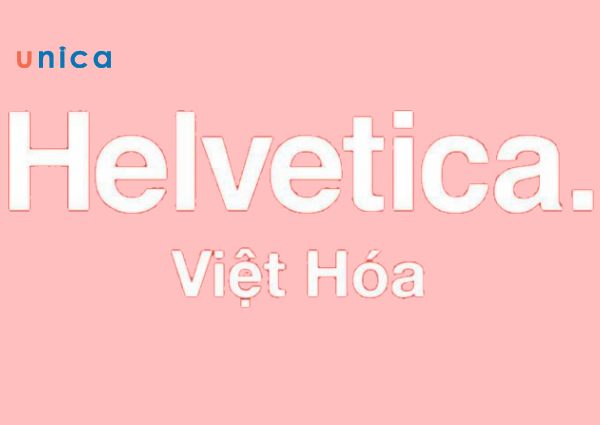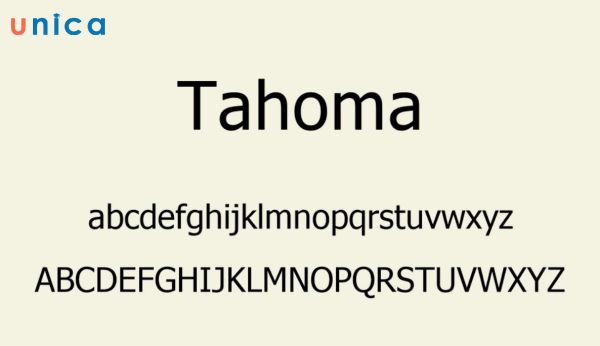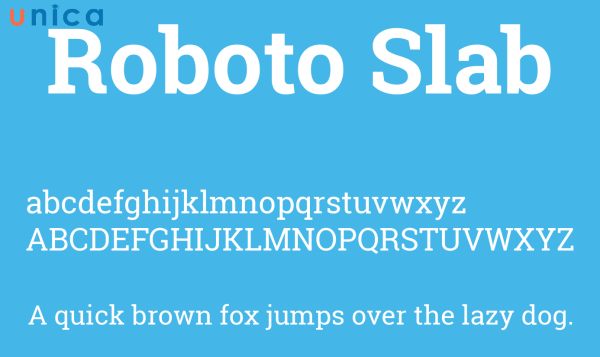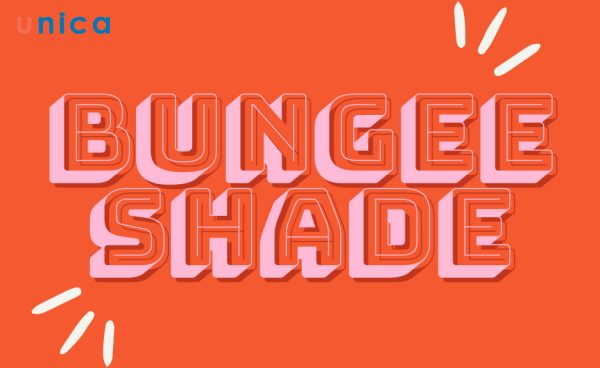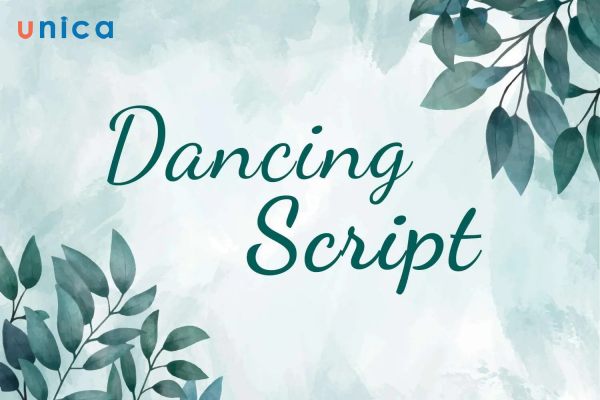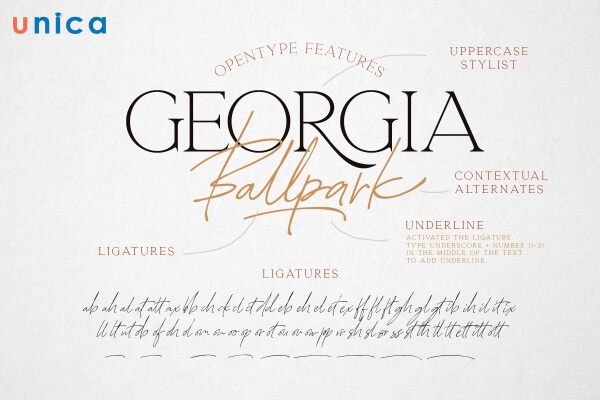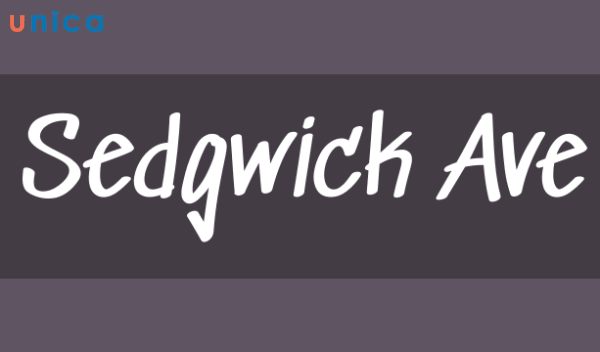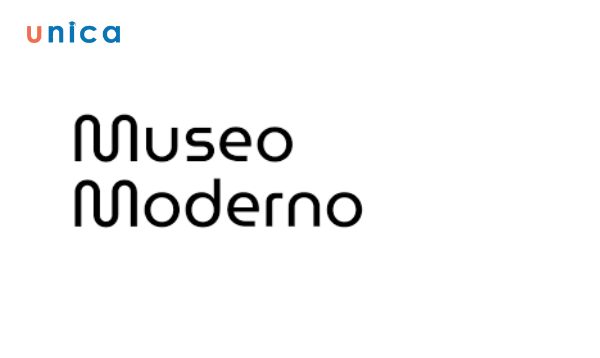
Top các font chữ đẹp tiếng việt giúp văn bản đẹp, thu hút hơn
Bạn đang tìm kiếm các font chữ đẹp tiếng Việt để làm cho văn bản của bạn trở nên đẹp mắt, thu hút và chuyên nghiệp hơn? Bạn đang băn khoăn không biết nên chọn font chữ nào cho phù hợp với mục đích và nội dung của bạn? Bạn đang gặp phải những lỗi font chữ tiếng Việt khi sử dụng word? Nếu bạn có những thắc mắc này, hãy cùng theo dõi bài viết dưới đây để tìm hiểu về top các font chữ tiếng Việt năm 2023 giúp văn bản đẹp, thu hút hơn. Chúng tôi sẽ giới thiệu cho bạn về tầm quan trọng của việc lựa chọn font chữ đẹp trong word, giới thiệu một số font chữ tiếng Việt cho các loại văn bản khác nhau, chỉ ra những lỗi font chữ tiếng Việt thường gặp và đưa ra một số lưu ý khi lựa chọn font chữ đẹp. Hãy cùng bắt đầu nhé!
Tại sao cần phải lựa chọn Font chữ đẹp trong word?
Font chữ là một yếu tố quan trọng trong việc trình bày văn bản. Font chữ không chỉ ảnh hưởng đến thẩm mỹ của văn bản, mà còn ảnh hưởng đến tính hiệu quả, sự truyền tải và sự nhận thức của người đọc. Một số lý do để bạn cần phải lựa chọn font chữ đẹp trong word là:
Tăng tính ảnh hưởng và sự chuyên nghiệp
Font chữ có thể tạo ra một ấn tượng ban đầu cho người đọc về văn bản của bạn. Một font chữ đẹp sẽ giúp văn bản của bạn trở nên hấp dẫn, uy tín và chuyên nghiệp hơn. Ngược lại, một font chữ xấu sẽ làm giảm giá trị của văn bản, gây ra sự nhàm chán, thiếu tin cậy và thiếu tôn trọng cho người đọc.
Font chữ có thể tạo ra một ấn tượng ban đầu cho người đọc về văn bản
Tạo điểm nhấn và thể hiện cá tính
Font chữ cũng có thể giúp bạn tạo ra những điểm nhấn cho văn bản, làm nổi bật những thông tin quan trọng, những ý kiến cá nhân hoặc những cảm xúc của bạn. Bạn có thể sử dụng các font chữ khác nhau để thể hiện cá tính, phong cách và sở thích của bạn.
Ví dụ, bạn có thể dùng các font chữ hiện đại, sáng tạo và trẻ trung để thể hiện sự năng động và mới mẻ; hoặc bạn có thể dùng các font chữ cổ điển, thanh lịch và trang nhã để thể hiện sự sang trọng và tinh tế.
Tăng sự thu hút
Font chữ đẹp tiếng việt cũng có thể giúp bạn thu hút sự quan tâm và chú ý của người đọc. Một font chữ đẹp sẽ làm cho văn bản của bạn trở nên sinh động, phong phú và hấp dẫn hơn. Người đọc sẽ có xu hướng muốn đọc tiếp và khám phá thêm văn bản của bạn. Một font chữ xấu sẽ làm cho văn bản của bạn trở nên đơn điệu, tẻ nhạt và nhàm chán hơn. Người đọc sẽ có xu hướng bỏ qua hoặc bỏ dở văn bản của bạn.
Font chữ cũng có thể giúp bạn thu hút sự quan tâm và chú ý của người đọc
Giới thiệu một số font chữ đẹp tiếng Việt
Trên word, bạn có thể tìm thấy rất nhiều font chữ đẹp tiếng Việt cho các loại văn bản khác nhau. Dưới đây là một số font chữ tiếng Việt mà chúng tôi muốn giới thiệu cho bạn:
Phông chữ đẹp trong word dành cho văn bản
Nếu bạn muốn viết các loại văn bản như báo cáo, luận văn, bài viết, thư từ, email,… bạn nên chọn các font chữ dễ đọc, rõ ràng và trang trọng. Một số font chữ đẹp trong word dành cho văn bản là:
Be Vietnam
Be Vietnam là một font chữ sans serif được thiết kế bởi Nguyễn Đức Hiếu. Font chữ này có 8 kiểu khác nhau, từ Extra Light đến Extra Bold. Font chữ này có thể hỗ trợ tiếng Việt và nhiều ngôn ngữ khác. Font chữ đẹp word này có dáng vẻ hiện đại, thanh thoát và cân đối. Font chữ này phù hợp cho các văn bản mang tính truyền thông, quảng cáo và thương mại.
Be Vietnam là một font chữ sans serif được thiết kế bởi Nguyễn Đức Hiếu
Open Sans
Open Sans là một font chữ sans serif được thiết kế bởi Steve Matteson. Font chữ đẹp tiếng việt này có 10 kiểu khác nhau, từ Light đến Extra Bold. Font chữ này có thể hỗ trợ tiếng Việt và nhiều ngôn ngữ khác. Open Sans có dáng vẻ trung tính, thân thiện và linh hoạt. Font chữ này phù hợp cho các văn bản mang tính thông tin, giáo dục và khoa học.
Roboto
Roboto là một trong số các font chữ tiếng việt đẹp có sẵn trong word, nó thuộc font chữ sans serif được thiết kế bởi Christian Robertson. Font chữ này có 12 kiểu khác nhau, từ Thin đến Black. Font chữ này có thể hỗ trợ tiếng Việt và nhiều ngôn ngữ khác. Roboto có dáng vẻ hiện đại, rõ ràng và tự nhiên nên phù hợp cho các văn bản mang tính công nghệ, kỹ thuật và kinh doanh.
Roboto có dáng vẻ hiện đại, rõ ràng và tự nhiên
Source Sans Pro
Source Sans Pro là một font chữ sans serif được thiết kế bởi Paul D. Hunt. Font chữ này có 12 kiểu khác nhau, từ Extra Light đến Black. Font chữ này có thể hỗ trợ tiếng Việt và nhiều ngôn ngữ khác. Font chữ này có dáng vẻ đơn giản, thanh lịch và hiệu quả. Source Sans Pro phù hợp cho các văn bản mang tính sáng tạo, nghệ thuật và văn hóa.
word
Playfair Display
Playfair Display là một font chữ serif được thiết kế bởi Claus Eggers Sørensen. Font chữ đẹp tiếng việt này có 6 kiểu khác nhau, từ Regular đến Black. Font chữ này có thể hỗ trợ tiếng Việt và nhiều ngôn ngữ khác. Font này có dáng vẻ cổ điển, sang trọng và quý phái nên phù hợp cho các văn bản mang tính lịch sử, văn học và thời trang.
Playfair Display là một font chữ serif được thiết kế bởi Claus Eggers Sørensen
Bookman
Bookman là một font chữ serif được thiết kế bởi Alexander Phemister. Font chữ này có 4 kiểu khác nhau, từ Regular đến Bold Italic. Font chữ này có thể hỗ trợ tiếng Việt và nhiều ngôn ngữ khác. Font chữ này có dáng vẻ truyền thống, tinh tế và uyển chuyển. Font chữ Bookman phù hợp cho các văn bản mang tính giáo dục, tri thức và báo chí.
Museo Moderno
Museo Moderno là một font chữ serif được thiết kế bởi Omnibus-Type. Font chữ này có 14 kiểu khác nhau, từ Thin đến Heavy. Font chữ này có thể hỗ trợ tiếng Việt và nhiều ngôn ngữ khác. Font chữ này có dáng vẻ hiện đại, độc đáo và nghệ thuật. Font chữ này phù hợp cho các văn bản mang tính sáng tạo, thiết kế và nghệ thuật.
Museo Moderno là một font chữ serif được thiết kế bởi Omnibus-Type
Noto Serif
Noto Serif là một font chữ serif được thiết kế bởi Google. Font chữ này có 4 kiểu khác nhau, từ Regular đến Bold Italic. Font chữ này có thể hỗ trợ tiếng Việt và nhiều ngôn ngữ khác. Font chữ đẹp tiếng việt này có dáng vẻ đa dạng, cân bằng và hài hòa nên phù hợp cho các văn bản mang tính đa văn hóa, đa ngôn ngữ và đa phương tiện.
Sedgwick Ave
Sedgwick Ave là một font chữ handwritten được thiết kế bởi Google. Font chữ này có 2 kiểu khác nhau là Regular và Display. Font chữ này có thể hỗ trợ tiếng Việt và nhiều ngôn ngữ khác. Font chữ này có dáng vẻ thân thiện, gần gũi và cá nhân nên phù hợp cho các văn bản mang tính giao tiếp, thư từ và blog.
Sedgwick Ave là một font chữ handwritten được thiết kế bởi Google
Amatic SC
Amatic SC là một font chữ viết tay trong word được thiết kế bởi Vernon Adams và Ben Nathan. Font chữ này có 2 kiểu khác nhau là Regular và Bold. Font chữ này có thể hỗ trợ tiếng Việt và nhiều ngôn ngữ khác. Amatic SC này có dáng vẻ độc lập, sôi nổi và năng động nên phù hợp cho các văn bản mang tính giải trí, du lịch hoặc nội dung viết cho trẻ em.
Patrick Hand
Patrick Hand là một font chữ handwritten được thiết kế bởi Patrick Wagesreiter. Font chữ này chỉ có một kiểu duy nhất là Regular. Patrick Hand có thể hỗ trợ tiếng Việt và nhiều ngôn ngữ khác. Font chữ này có dáng vẻ tự nhiên, dễ thương và lãng mạn. Font chữ đẹp tiếng việt này phù hợp cho các văn bản mang tính cảm xúc, tình cảm và nhật ký.
Patrick Hand là một font chữ handwritten được thiết kế bởi Patrick Wagesreiter
Courier new
Courier new là một font chữ monospaced được thiết kế bởi Howard Kettler. Font chữ này có 4 kiểu khác nhau, từ Regular đến Bold Italic. Courier new có thể hỗ trợ tiếng Việt và nhiều ngôn ngữ khác. Font chữ này có dáng vẻ cổ điển, chính thức và chuyên nghiệp. Font chữ này phù hợp cho các văn bản mang tính kỹ thuật, lập trình và tài liệu.
Verdana
Verdana là một font chữ sans serif được thiết kế bởi Matthew Carter. Phông chữ tiếng việt trong word này có 4 kiểu khác nhau, từ Regular đến Bold Italic. Font chữ này có thể hỗ trợ tiếng Việt và nhiều ngôn ngữ khác. Font chữ này đem tới cảm giác rộng rãi, minh bạch và dễ đọc. Font chữ đẹp tiếng việt Verdana phù hợp cho các văn bản mang tính trực quan, trình chiếu và web.
Georgia
Trong số các font chữ tiếng việt trong word, Georgia là một font chữ serif được thiết kế bởi Matthew Carter. Font chữ này có 4 kiểu khác nhau, từ Regular đến Bold Italic. Font chữ này có thể hỗ trợ tiếng Việt và nhiều ngôn ngữ khác. Font chữ này có dáng vẻ cổ điển, thanh thoát và tao nhã nên phù hợp cho các văn bản mang tính văn học, văn hóa và nghệ thuật.
Georgia là một font chữ serif được thiết kế bởi Matthew Carter
Các kiểu chữ đẹp trong word cho thiết kế
Nếu bạn muốn thiết kế các loại văn bản như poster, banner, logo, slogan,… bạn nên chọn các font chữ độc đáo, sáng tạo và ấn tượng. Một số font chữ đẹp trong word cho thiết kế là:
Bangers
Bangers là một font chữ comic được thiết kế bởi Vernon Adams. Font chữ này chỉ có một kiểu duy nhất là Regular. Font chữ đẹp tiếng việt này có thể hỗ trợ tiếng Việt và nhiều ngôn ngữ khác. Bangers có kiểu dáng mạnh mẽ, nổi bật và hài hước. Font chữ này phù hợp cho các văn bản mang tính giải trí, hoạt hình và game.
Bangers là một font chữ comic được thiết kế bởi Vernon Adams
Lobster
Lobster là một font chữ script được thiết kế bởi Pablo Impallari. Font chữ này chỉ có một kiểu duy nhất là Regular. Lobster có thể hỗ trợ tiếng Việt và nhiều ngôn ngữ khác. Font chữ này có dáng vẻ uốn lượn, duyên dáng và lôi cuốn nên phù hợp cho các văn bản viết về thời trang, ẩm thực hoặc lễ hội.
Dancing Script
Trong số các kiểu chữ đẹp trong word, Dancing Script là một font chữ script được thiết kế bởi Impallari Type. Font chữ này có 2 kiểu khác nhau là Regular và Bold. Font chữ này có thể hỗ trợ tiếng Việt và nhiều ngôn ngữ khác. Dancing Script có dáng vẻ hiện đại, rõ ràng và linh hoạt. Font chữ đẹp tiếng việt này phù hợp cho các tài liệu mang tính công nghệ, kỹ thuật và kinh doanh.
Dancing Script là một font chữ script được thiết kế bởi Impallari Type
Pacifico
Pacifico là một font chữ tiếng Việt thân thiện và phong cách, thích hợp cho các tiêu đề, tiêu đề trang và các yếu tố thiết kế sáng tạo khác. Với đường nét mềm mại và hiện đại, Pacifico thường được sử dụng trong các thiết kế liên quan đến nghệ thuật, thẩm mỹ và phong cách cá nhân.
Bungee Shade
Bungee Shade là một font chữ tiếng Việt độc đáo và nổi bật với những nét chữ hình khối. Với sự kết hợp của các đường nét mạnh mẽ và sự sáng tạo trong thiết kế, Bungee Shade thường được ưa chuộng trong các dự án liên quan đến thiết kế đồ họa và trang trí.
Bungee Shade là một font chữ tiếng Việt độc đáo và nổi bật với những nét chữ hình khối
Saira Stencil One
Saira Stencil One là một font chữ đẹp tiếng Việt mang phong cách stencil, tạo nên sự độc đáo và nổi bật trong các thiết kế. Với các đường nét mạnh mẽ và kiểu chữ đặc biệt, Saira Stencil One thường được sử dụng để tạo điểm nhấn và tạo sự khác biệt trong các dự án thiết kế.
Srisakdi
Srisakdi là một font chữ tiếng Việt mang phong cách hiện đại và sáng tạo. Với các đường nét thanh lịch và hiện đại, Srisakdi thường được sử dụng trong các văn bản và bài thuyết trình để tạo nên sự chuyên nghiệp và sáng tạo.
Charmonman
Charmonman là một font chữ tiếng Việt với nét đẹp truyền thống và thanh lịch. Với các đường nét uốn cong và phong cách tinh tế, Charmonman thường được ưa chuộng trong các tài liệu văn bản, thư mời và các thiết kế liên quan đến văn hóa truyền thống.
Charmonman là một font chữ tiếng Việt với nét đẹp truyền thống và thanh lịch
Font chữ đẹp trên Word dành cho dân văn phòng
Dành cho dân văn phòng, việc chọn font chữ phù hợp là rất quan trọng để tạo ra văn bản chuyên nghiệp và dễ đọc. Một trong những font chữ phổ biến dành cho dân văn phòng trên Word là:
Font chữ Roboto Slab
Roboto Slab là một font chữ đẹp tiếng Việt đơn giản và dễ đọc, với các đường nét thanh lịch và chữ viết rõ ràng. Với phong cách hiện đại và trang nhã, Roboto Slab thường được sử dụng trong các tài liệu văn bản, báo cáo và tài liệu công việc.
Roboto Slab là một font chữ tiếng Việt đơn giản và dễ đọc, với các đường nét thanh lịch và chữ viết rõ ràng
Nhớ rằng, khi sử dụng font chữ trong Word, bạn cũng nên kiểm tra xem font đó có bản quyền sử dụng hay không để tuân thủ các quy định liên quan đến bản quyền phần mềm.
Font chữ Bitter
Bitter là một font chữ serif được thiết kế bởi Sol Matas. Font chữ này có 4 kiểu khác nhau, từ Regular đến Bold Italic. Bitter có thể hỗ trợ tiếng Việt và nhiều ngôn ngữ khác. Font chữ này có dáng vẻ cổ điển, thanh thoát và tao nhã nên phù hợp cho các tài liệu mang tính văn học, văn hóa và nghệ thuật.
Font chữ Lora
Lora là một font chữ serif được thiết kế bởi Cyreal. Font chữ đẹp tiếng việt này có 4 kiểu khác nhau, từ Regular đến Bold Italic. Font chữ này có thể hỗ trợ tiếng Việt và nhiều ngôn ngữ khác. Font chữ này có dáng vẻ trang nhã, cân bằng và hài hòa nên phù hợp cho các tài liệu mang tính thông tin, giáo dục và khoa học.
Lora là một font chữ serif được thiết kế bởi Cyreal
Times New Roman
Times New Roman là một font chữ serif được thiết kế bởi Stanley Morison. Font chữ này có 4 kiểu khác nhau, từ Regular đến Bold Italic. Font chữ này có thể hỗ trợ tiếng Việt và nhiều ngôn ngữ khác. Font chữ này có dáng vẻ truyền thống, chính thức và uy tín. Times New Roman phù hợp cho các tài liệu mang tính lịch sử, báo chí và tôn giáo.
Arial
Arial là một font chữ sans serif được thiết kế bởi Monotype Corporation. Font chữ đẹp tiếng việt này có 4 kiểu khác nhau, từ Regular đến Bold Italic. Font Arial có thể hỗ trợ tiếng Việt và nhiều ngôn ngữ khác. Font này có dáng vẻ đơn giản, minh bạch và dễ đọc nên phù hợp cho các tài liệu mang tính trực quan, trình chiếu và web.
Tahoma
Tahoma là một font chữ sans serif được thiết kế bởi Matthew Carter. Font chữ này có 2 kiểu khác nhau là Regular và Bold. Tahoma có thể hỗ trợ tiếng Việt và nhiều ngôn ngữ khác. Font chữ này khá rộng, tính chất linh hoạt nên phù hợp cho các tài liệu mang tính đa nền tảng, đa thiết bị và đa ngôn ngữ.
Tahoma là một font chữ sans serif được thiết kế bởi Matthew Carter
Calibri
Trong số những font chữ đẹp trong word, Calibri là một font chữ sans serif được thiết kế bởi Lucas de Groot. Font chữ này có 6 kiểu khác nhau, từ Light đến Bold Italic. Calibri có thể hỗ trợ tiếng Việt và nhiều ngôn ngữ khác. Font chữ đẹp tiếng việt này có dáng vẻ hiện đại, thanh lịch và trang nhã nên phù hợp cho các tài liệu mang tính sáng tạo, nghệ thuật và văn hóa.
Garamond
Garamond là một font chữ serif được thiết kế bởi Claude Garamond. Font chữ này có 4 kiểu khác nhau, từ Regular đến Bold Italic. Font Garamond có thể hỗ trợ tiếng Việt và nhiều ngôn ngữ khác. Font chữ này có dáng vẻ cổ điển, tinh tế và quý phái nên đây sẽ là sự lựa chọn phù hợp cho các tài liệu mang tính lịch sử, văn học và thời trang.
Helvetica
Helvetica là một font chữ sans serif được thiết kế bởi Max Miedinger. Font chữ này có nhiều kiểu khác nhau, từ Ultra Light đến Black. Helvetica có thể hỗ trợ tiếng Việt và nhiều ngôn ngữ khác. Font chữ này có dáng vẻ đơn giản, minh bạch và dễ đọc nên phù hợp cho các tài liệu mang tính trực quan, trình chiếu và web.
Helvetica là một font chữ sans serif được thiết kế bởi Max Miedinger
Lỗi font chữ tiếng Việt thường gặp
Khi sử dụng font chữ đẹp tiếng Việt trong word, bạn có thể gặp phải một số lỗi font chữ tiếng Việt như sau:
Font không hỗ trợ tiếng Việt
Đây là lỗi font chữ tiếng Việt khi bạn sử dụng một font chữ không có bảng mã tiếng Việt hoặc không tương thích với bộ gõ tiếng Việt của bạn. Khi đó, bạn sẽ không thể nhập được các ký tự tiếng Việt như â, ă, ê, ô, ơ, ư, đ,… hoặc các ký tự có dấu như á, à, ả, ã, ạ,… Lỗi font chữ tiếng Việt này sẽ làm cho văn bản của bạn bị sai ngữ nghĩa, khó hiểu hoặc không thể hiển thị được.
Để khắc phục lỗi font chữ tiếng Việt này, bạn nên chọn một font chữ hỗ trợ tiếng Việt hoặc cài đặt thêm font chữ tiếng Việt cho word. Bạn cũng nên kiểm tra lại bộ gõ tiếng Việt của bạn để đảm bảo rằng nó tương thích với font chữ bạn đang sử dụng.
Font không hỗ trợ tiếng Việt
Hiển thị sai ký tự tiếng Việt
Đây là lỗi font chữ tiếng Việt khi bạn sử dụng một font chữ có bảng mã tiếng Việt khác với bảng mã tiếng Việt của word hoặc của máy tính của bạn. Khi đó, bạn sẽ thấy các ký tự tiếng Việt của bạn bị thay thế bởi các ký tự khác như ?, !, #,… hoặc các ký tự lạ như Æ, Ç, Ñ,… Lỗi font chữ tiếng Việt này sẽ làm cho văn bản của bạn bị mất nội dung, sai hình thức hoặc không thể hiển thị được.
Để khắc phục lỗi font chữ tiếng Việt này, bạn nên chọn một font chữ có cùng bảng mã tiếng Việt với word hoặc với máy tính của bạn. Bạn cũng nên kiểm tra lại cài đặt ngôn ngữ và khu vực của word và của máy tính của bạn để đảm bảo rằng chúng phù hợp với font chữ mình đang sử dụng.
>>> Tất cả đều có trong cuốn sách "Sách hướng dẫn thực hành Word từ cơ bản đến nâng cao"
[blog_custom:3]
[trial-btn-v4[link=https://unica.vn/order/step1?id=2850&quantity=1][text=ĐĂNG KÝ MUA NGAY][color=#ffffff][width=275px][height=50px][bgcolor=#f26c50][newtab=true]]
Kích thước và khoảng cách chữ không chuẩn
Đây là lỗi font chữ tiếng Việt khi bạn sử dụng một font chữ có kích thước và khoảng cách chữ không phù hợp với văn bản của mình. Khi đó, bạn sẽ thấy các ký tự tiếng Việt của bạn bị quá lớn hoặc quá nhỏ, quá dày hoặc quá mỏng, quá gần hoặc quá xa nhau. Lỗi font chữ tiếng Việt này sẽ làm cho văn bản của bạn bị mất thẩm mỹ, khó đọc hoặc không đồng đều.
Để khắc phục lỗi này, bạn nên điều chỉnh kích thước và khoảng cách chữ của font đang sử dụng cho phù hợp với văn bản. Bạn có thể sử dụng các công cụ như Font, Paragraph, Styles và Format Painter trong word để thực hiện điều này. Bạn cũng nên lựa chọn một font chữ có kích thước và khoảng cách chữ chuẩn cho văn bản.
Font chữ có kích thước gặp vấn đề
Vấn đề không tương thích giữa các máy tính
Đây là lỗi font chữ tiếng Việt khi bạn gửi hoặc nhận văn bản từ một máy tính khác có cài đặt font chữ khác với máy tính của bạn. Khi đó, bạn sẽ thấy văn bản của bạn bị thay đổi font chữ, mất nội dung hoặc không thể hiển thị được trên máy tính khác. Lỗi font chữ tiếng Việt này sẽ làm cho văn bản của bạn bị mất tính nhất quán, độ tin cậy và khả năng truyền tải.
Để khắc phục lỗi font chữ tiếng Việt này, bạn nên gửi hoặc nhận văn bản dưới dạng PDF hoặc ảnh để đảm bảo rằng font chữ của bạn được giữ nguyên trên các máy tính khác. Bạn cũng nên sử dụng các font chữ tiêu chuẩn hoặc phổ biến để đảm bảo rằng các máy tính khác có thể hỗ trợ font chữ của mình.
Thiếu font chữ phù hợp
Đây là lỗi font chữ tiếng Việt khi bạn không tìm được một font chữ phù hợp với mục đích và nội dung của văn bản của bạn. Khi đó, bạn sẽ không thể tạo ra một văn bản đẹp mắt, thu hút và chuyên nghiệp. Lỗi font chữ tiếng Việt này sẽ làm cho văn bản của bạn bị thiếu sức sống, sáng tạo và ấn tượng.
Bạn nên tìm kiếm và cài đặt thêm các font chữ đẹp tiếng Việt cho word để có thể sử dụng chúng cho các văn bản của bạn. Bạn có thể tìm kiếm và cài đặt các font chữ đẹp tiếng Việt từ các trang web uy tín và miễn phí như Google Fonts, Font Squirrel, Dafont,…
Thiếu font chữ phù hợp
Một số lưu ý khi lựa chọn font chữ đẹp
Khi lựa chọn font chữ đẹp cho word, bạn nên chú ý đến một số yếu tố sau:
• Dễ đọc, dễ nhìn: Một font chữ đẹp là một font chữ dễ đọc, dễ nhìn cho người đọc. Bạn nên chọn một font chữ có kích thước, khoảng cách và độ rõ ràng phù hợp với văn bản của bạn. Bạn nên tránh sử dụng các font chữ quá nhỏ, quá lớn, quá dày, quá mỏng, quá gần, quá xa hoặc quá khó nhận biết.
Một font chữ đẹp là một font chữ dễ đọc, dễ nhìn cho người đọc
• Phù hợp: Một mẫu chữ đẹp trong word là một font chữ phù hợp với mục đích và nội dung của văn bản của bạn. Bạn nên chọn một font chữ có phong cách, tính cách và ý nghĩa hợp với văn bản của bạn. Bạn nên tránh sử dụng các font chữ không liên quan, không thích hợp hoặc gây hiểu lầm cho người đọc.
• Có sự thống nhất: Một font chữ đẹp tiếng Việt là một font chữ có sự thống nhất trong văn bản của bạn. Bạn nên sử dụng một hoặc hai font chữ cho toàn bộ văn bản của bạn. Bạn cũng nên tránh sử dụng quá nhiều font chữ khác nhau trong cùng một văn bản, gây ra sự rối rắm, loạn lạc và mất tính nhất quán.
>> Xem thêm: 3 Cách đổi chữ thường thành chữ hoa trong Word
• Nên dùng font tiêu chuẩn: Một font tiếng Việt đẹp là một font chữ tiêu chuẩn hoặc phổ biến cho word. Bạn nên sử dụng các font chữ tiêu chuẩn hoặc phổ biến để đảm bảo rằng văn bản của bạn có thể được hiển thị và in ấn một cách chính xác và đồng nhất trên các máy tính khác nhau. Bạn nên tránh sử dụng các font chữ quá lạ, quá hiếm hoặc quá mới, gây ra sự không tương thích, không hỗ trợ hoặc không hiển thị được trên các máy tính khác.
Một font chữ đẹp là một font chữ tiêu chuẩn hoặc phổ biến cho word
Kết luận
Như vậy, trong bài viết này, chúng tôi đã giới thiệu cho bạn về top các font chữ đẹp tiếng Việt năm 2023 giúp văn bản đẹp, thu hút hơn. Unica đã chỉ ra tầm quan trọng của việc lựa chọn font chữ đẹp trong word, giới thiệu một số font chữ đẹp tiếng Việt cho các loại văn bản khác nhau, chỉ ra những lỗi font chữ tiếng Việt thường gặp và đưa ra một số lưu ý khi lựa chọn font chữ đẹp. Hy vọng bài viết của chúng tôi đã giúp ích cho bạn trong việc tìm kiếm và sử dụng font chữ đẹp cho word. Đừng quên ghé qua các khóa học word online trên Unica nhé.